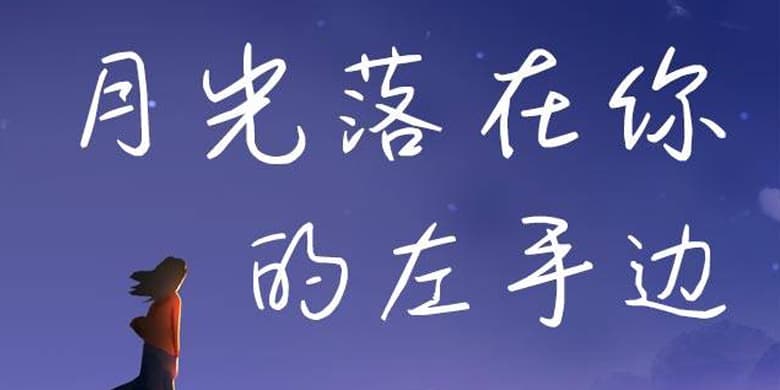
方正手迹-月光落在你的左手边
品牌:方正手迹设计师:罗晓康发行时间:2020字库编码:简繁扩展(GBK)分类:常规书写·硬笔字体属性:精品字
月光落在你的左手边是一款风格独特的手写体。该字体整体偏行草风,笔画连贯流畅曲线较多,体现出快速书写的快意感觉。适用于文艺类的书刊、品牌广告和产品包装设计,以及社交网络的个性化用字。